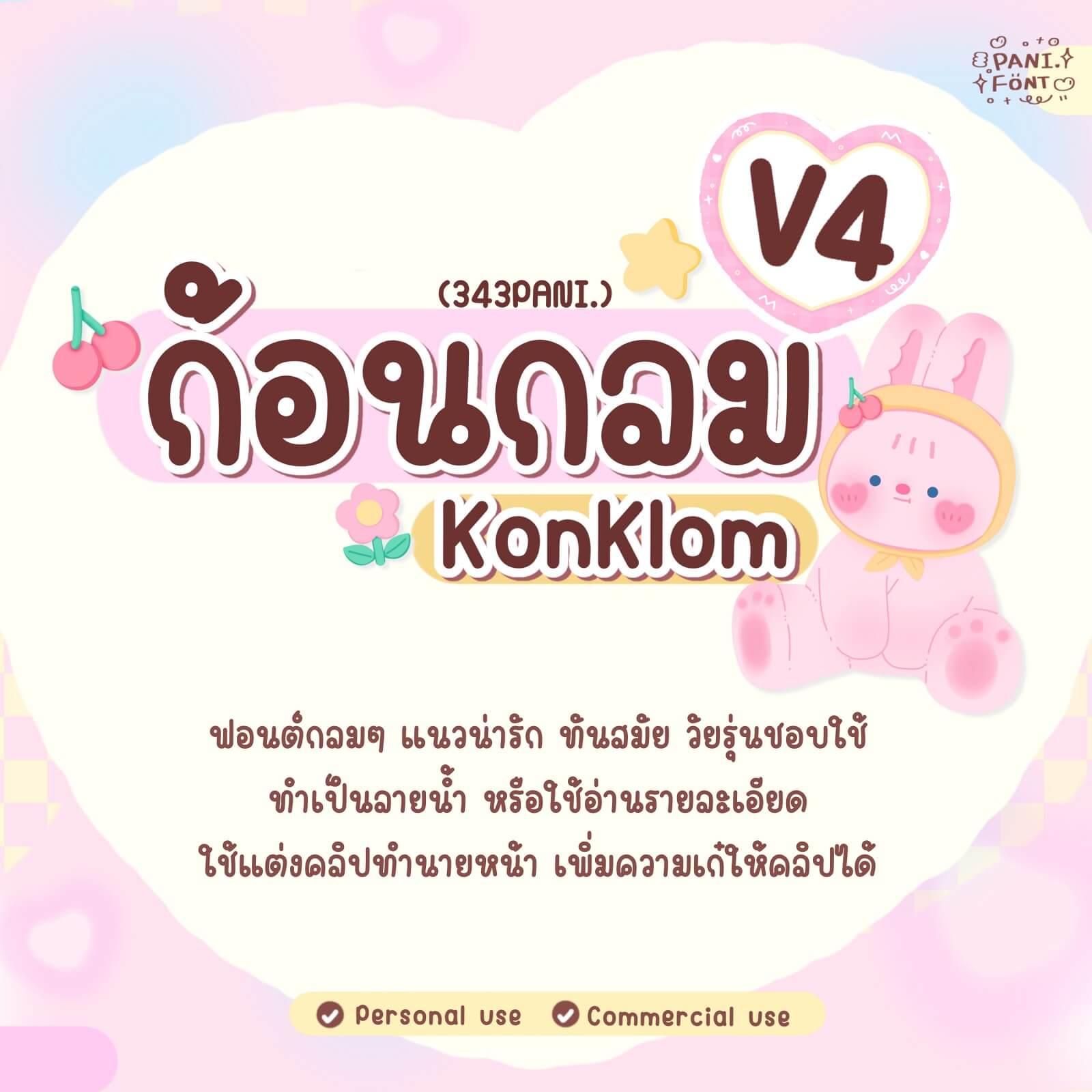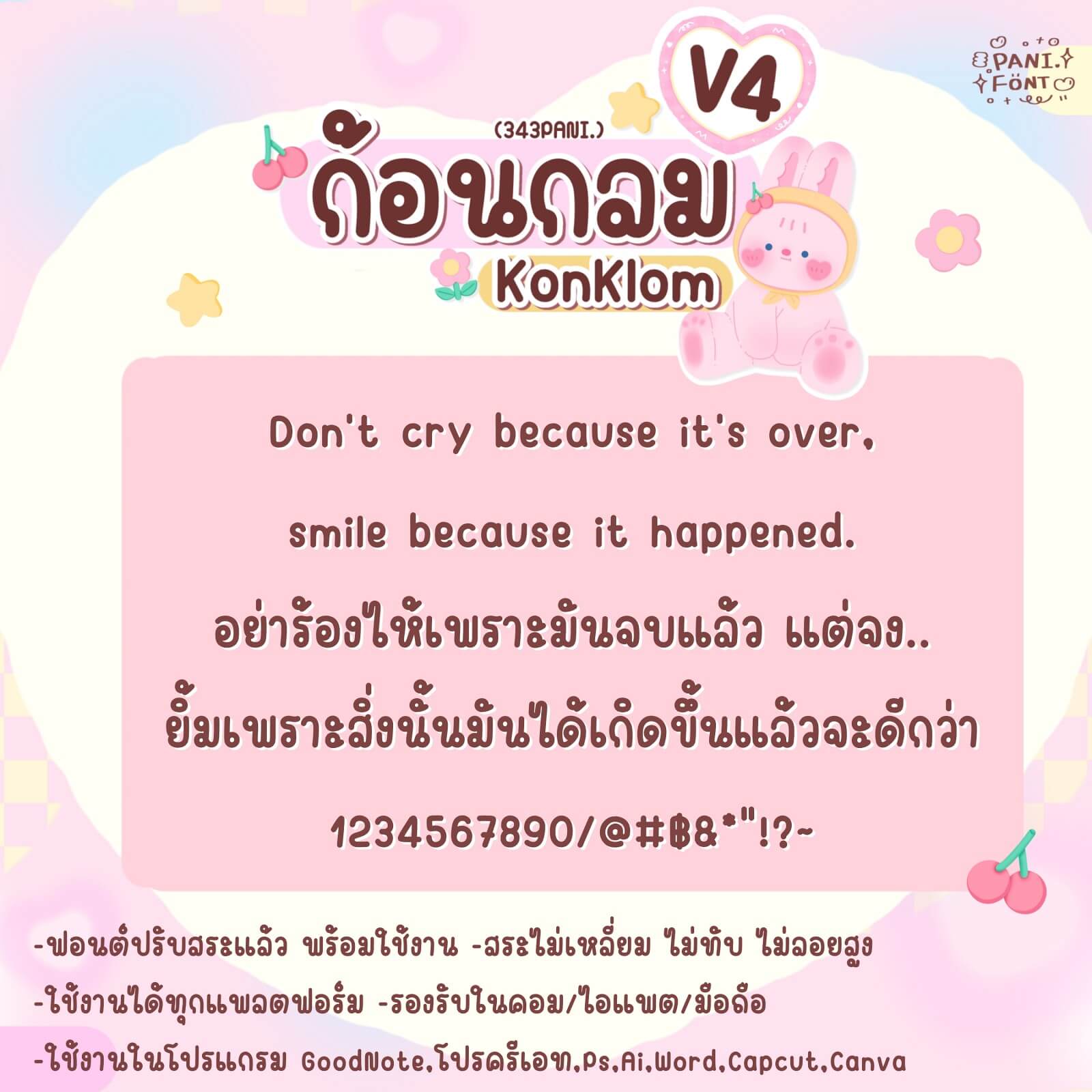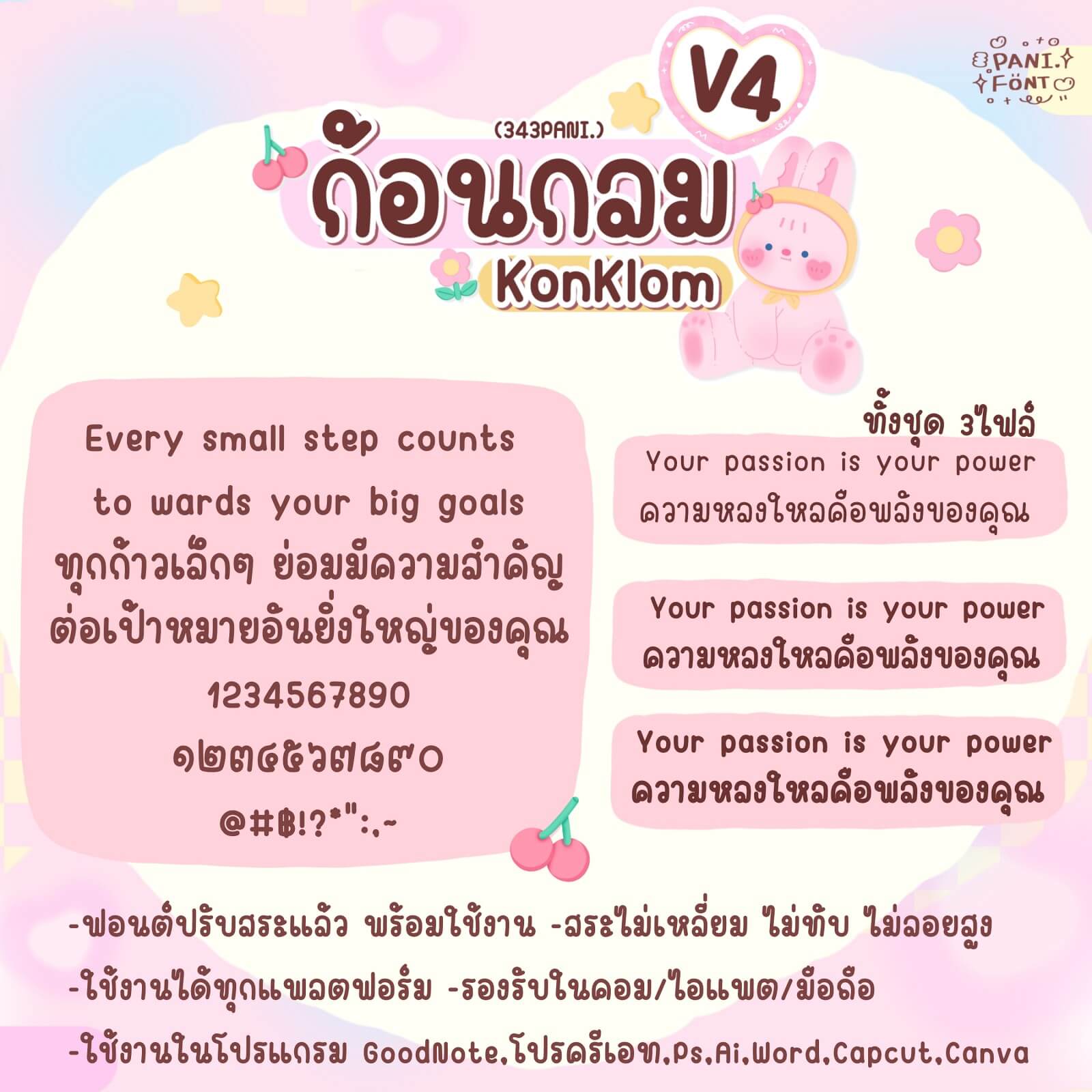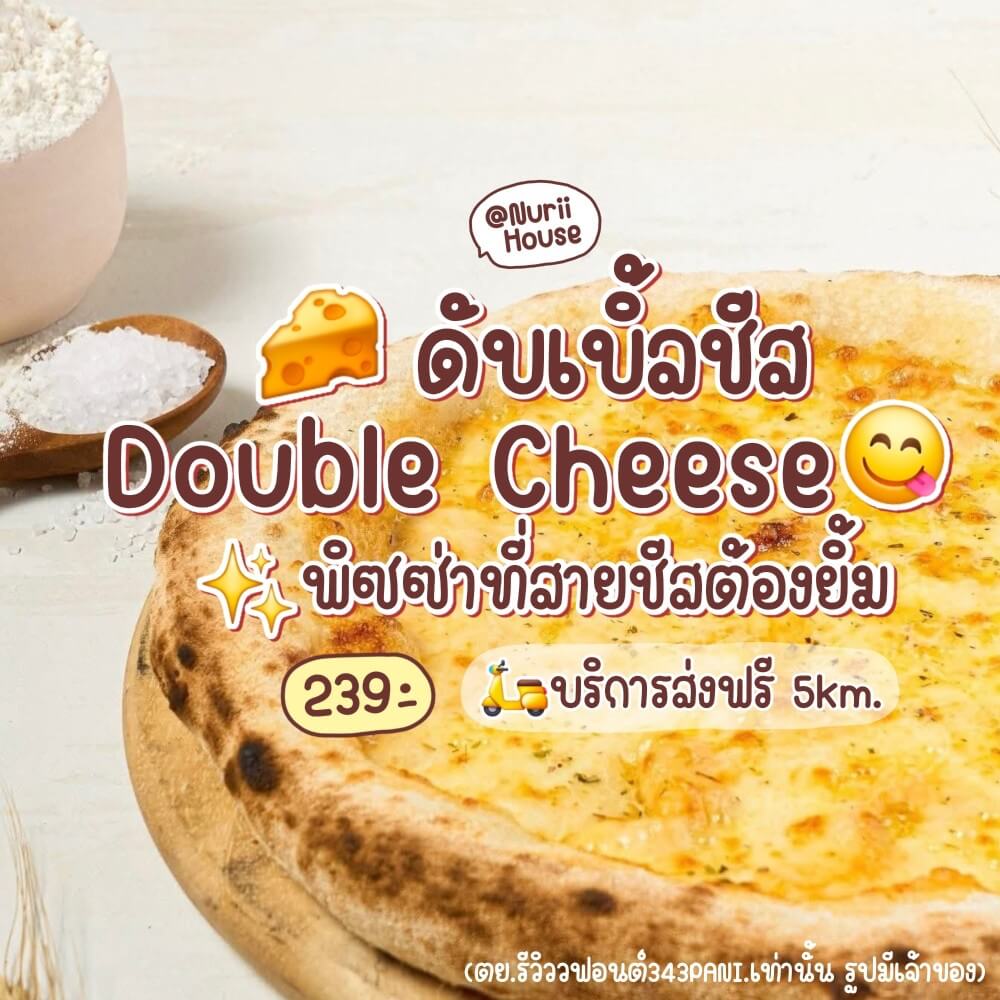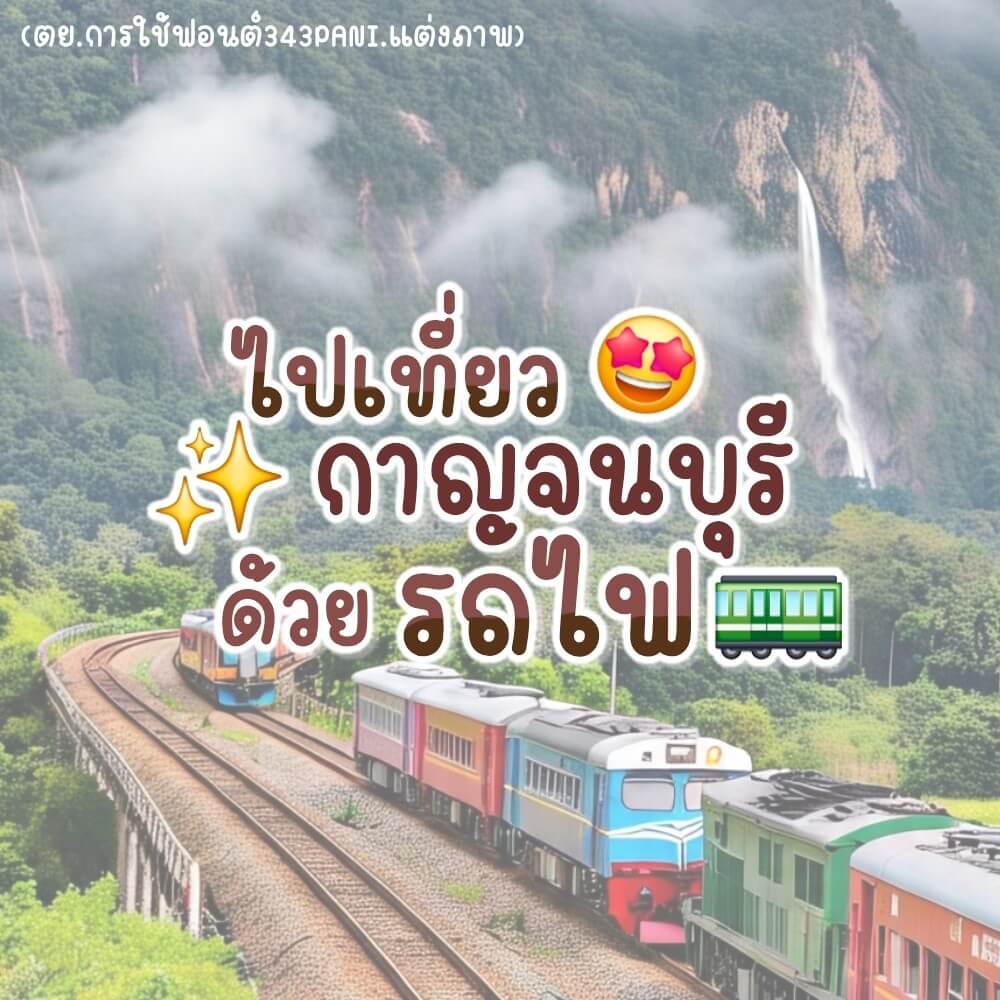
ฟอนต์ 343PANI.ก้อนกลมV4 – โหลดทดลองใช้ฟรีตัว Demo ฟอนต์กลมๆ แนวน่ารัก ทันสมัย วัยรุ่นชอบใช้ ทำเป็นลายน้ำ หรือใช้อ่านรายละเอียด ใช้แต่งคลิป ทำรูปสินค้า ทำนายหน้า เพิ่มความเก๋ให้คลิปได้
343PANI.ก้อนกลมV4